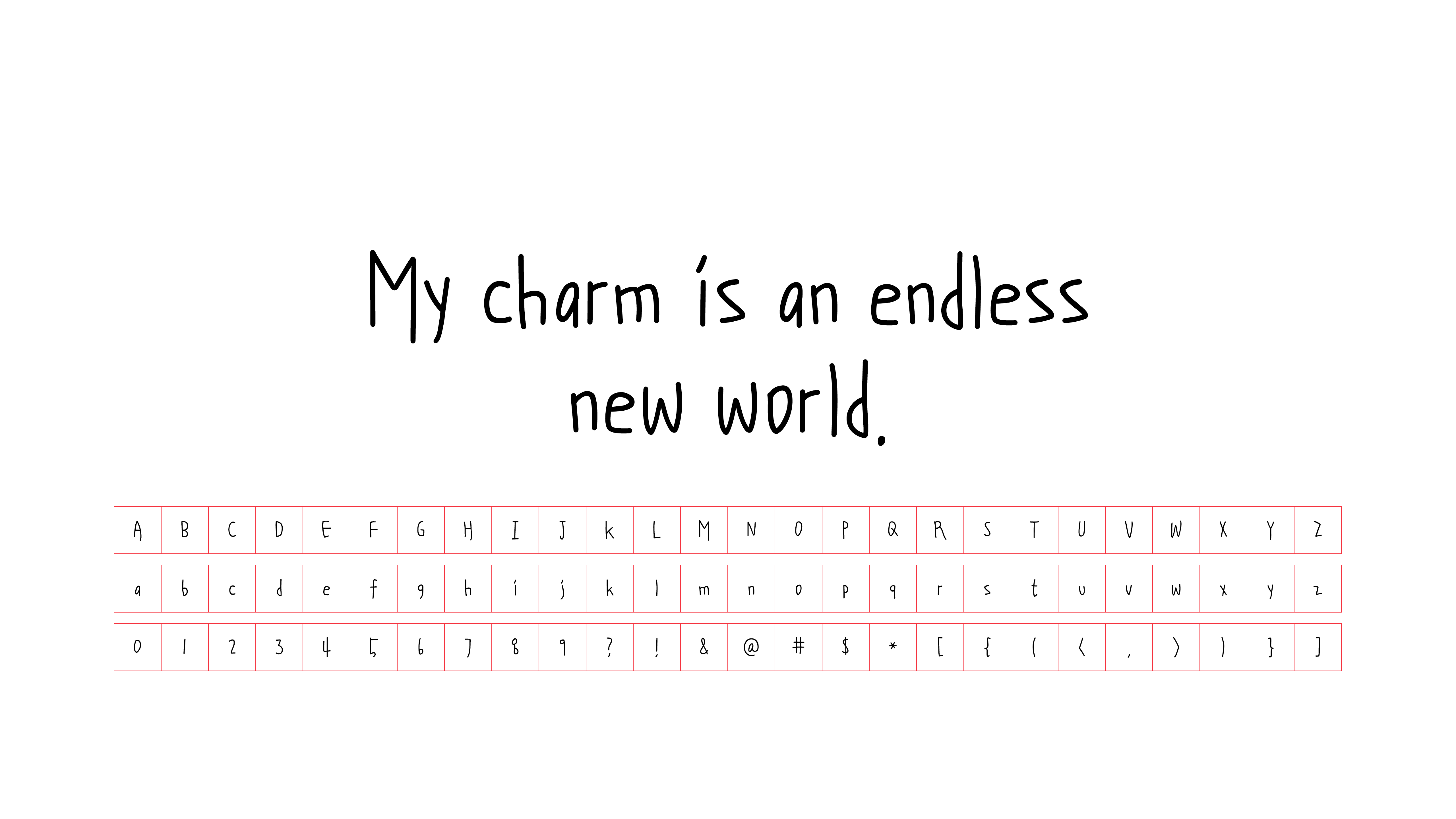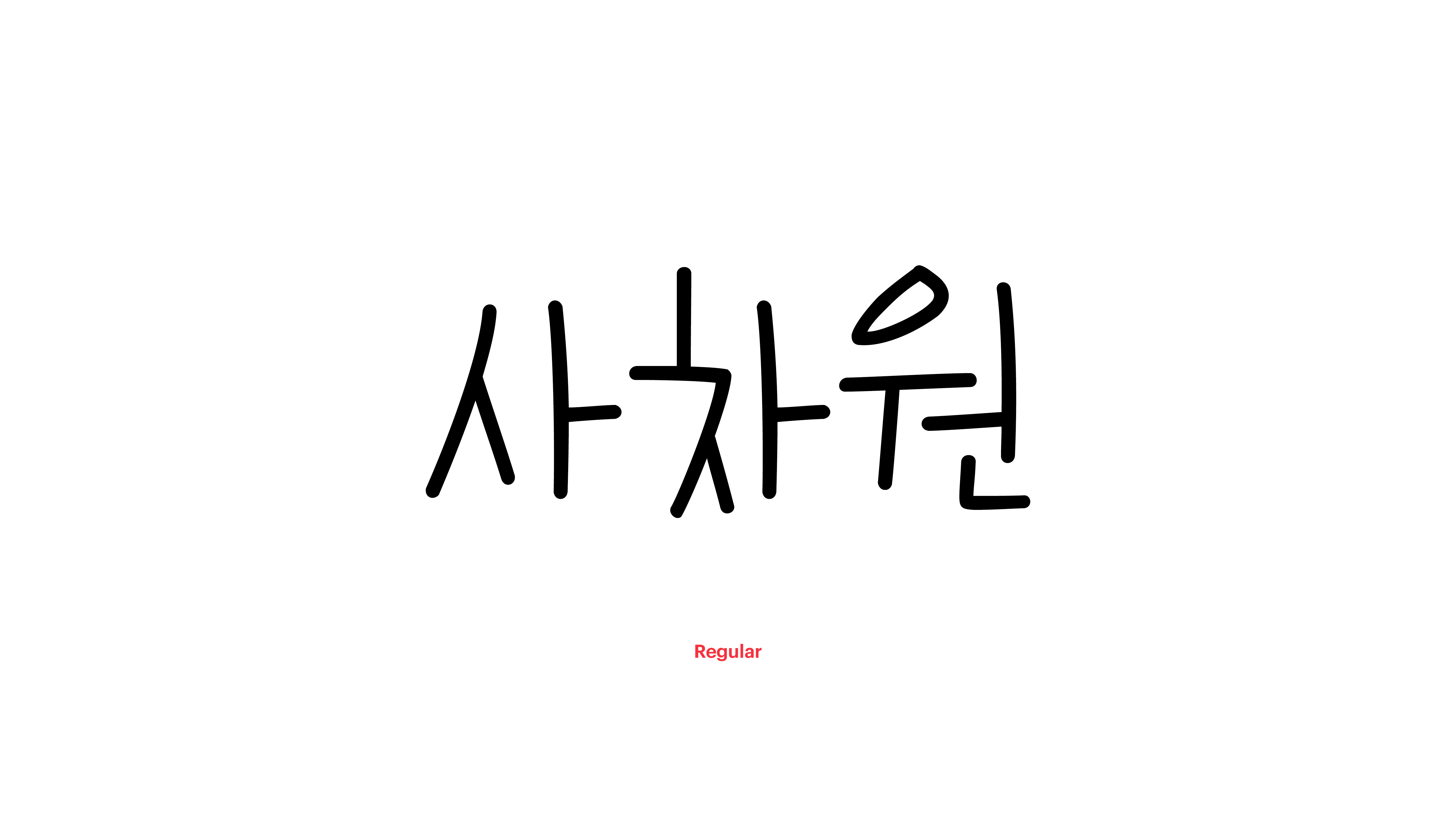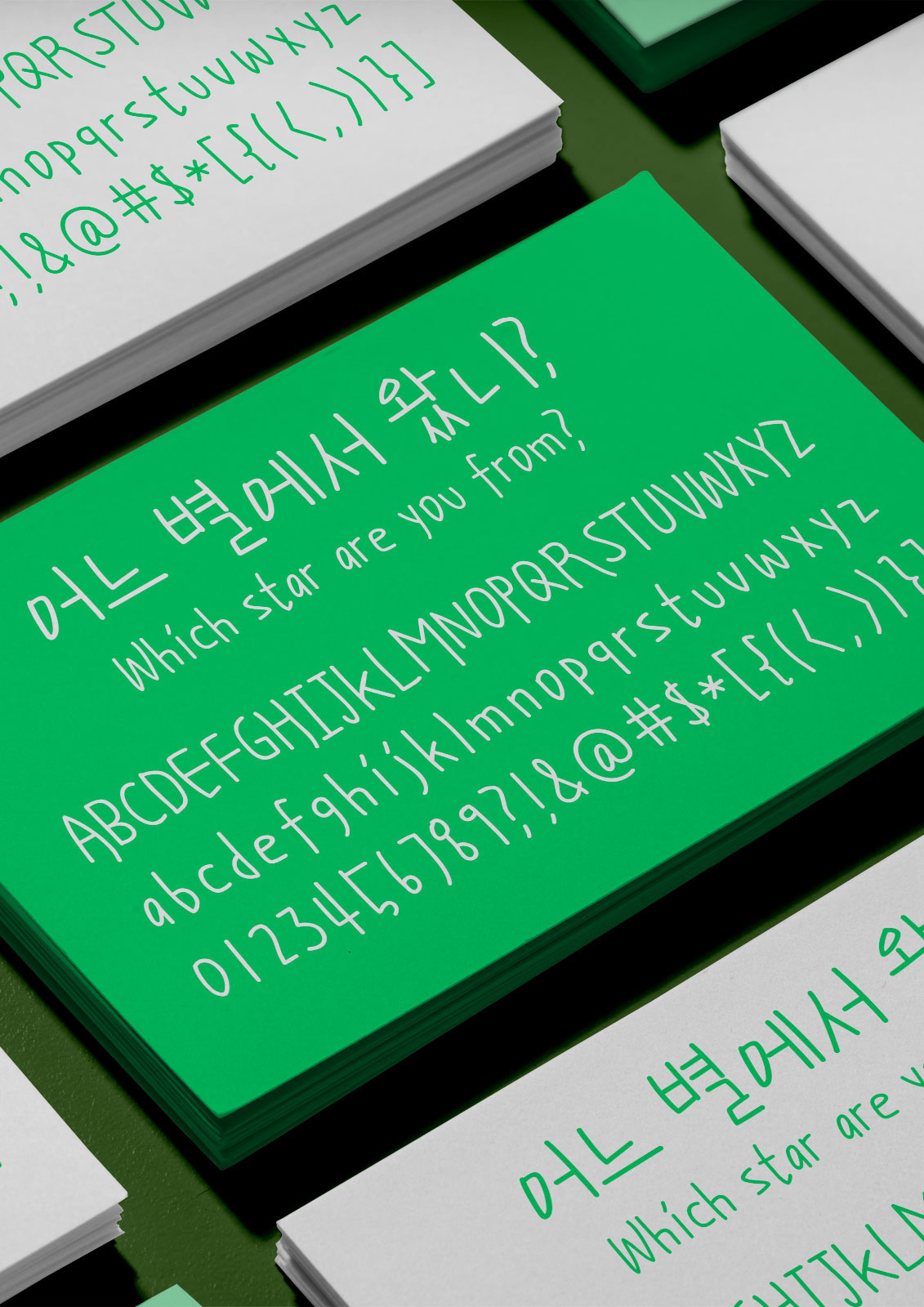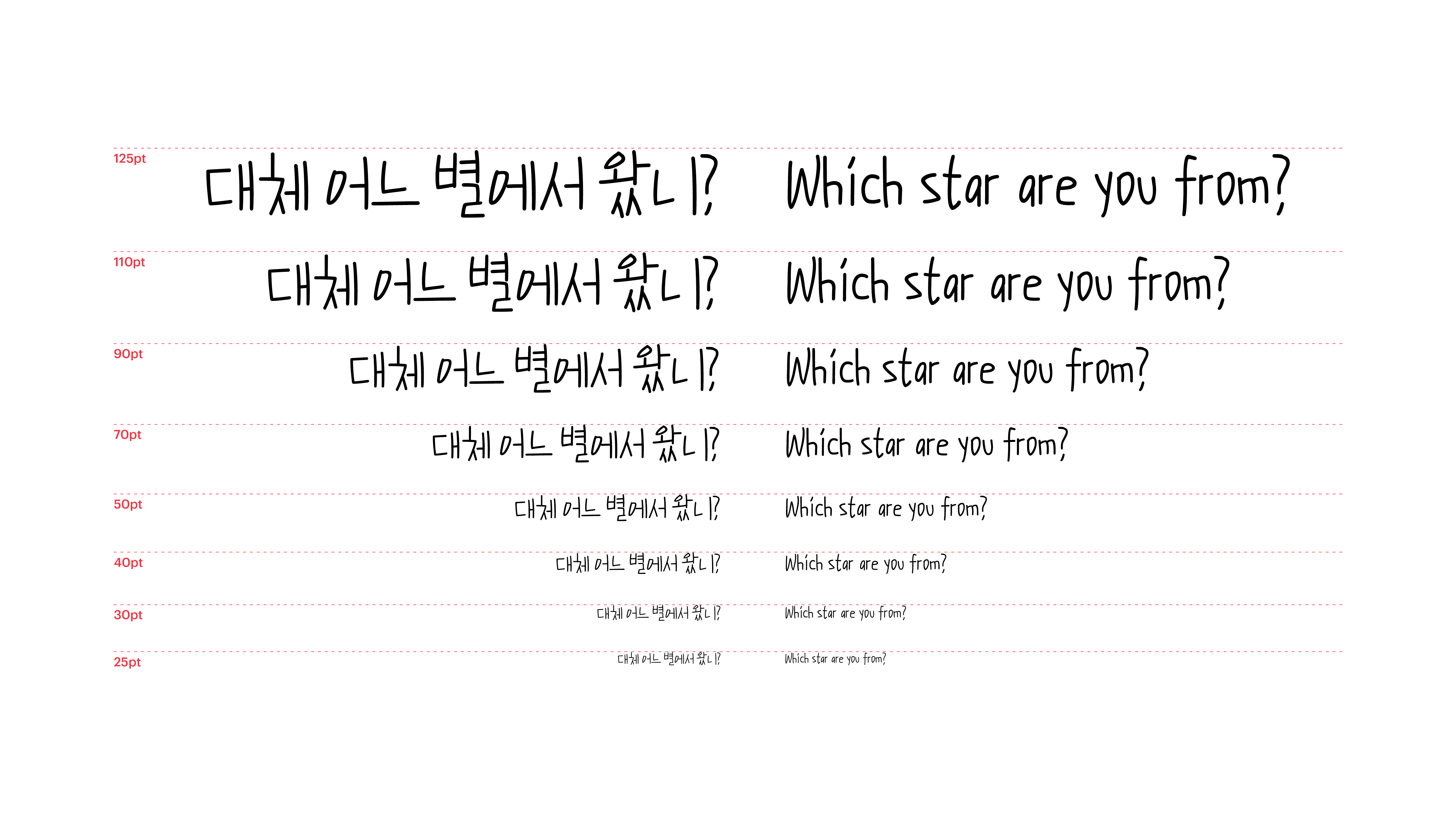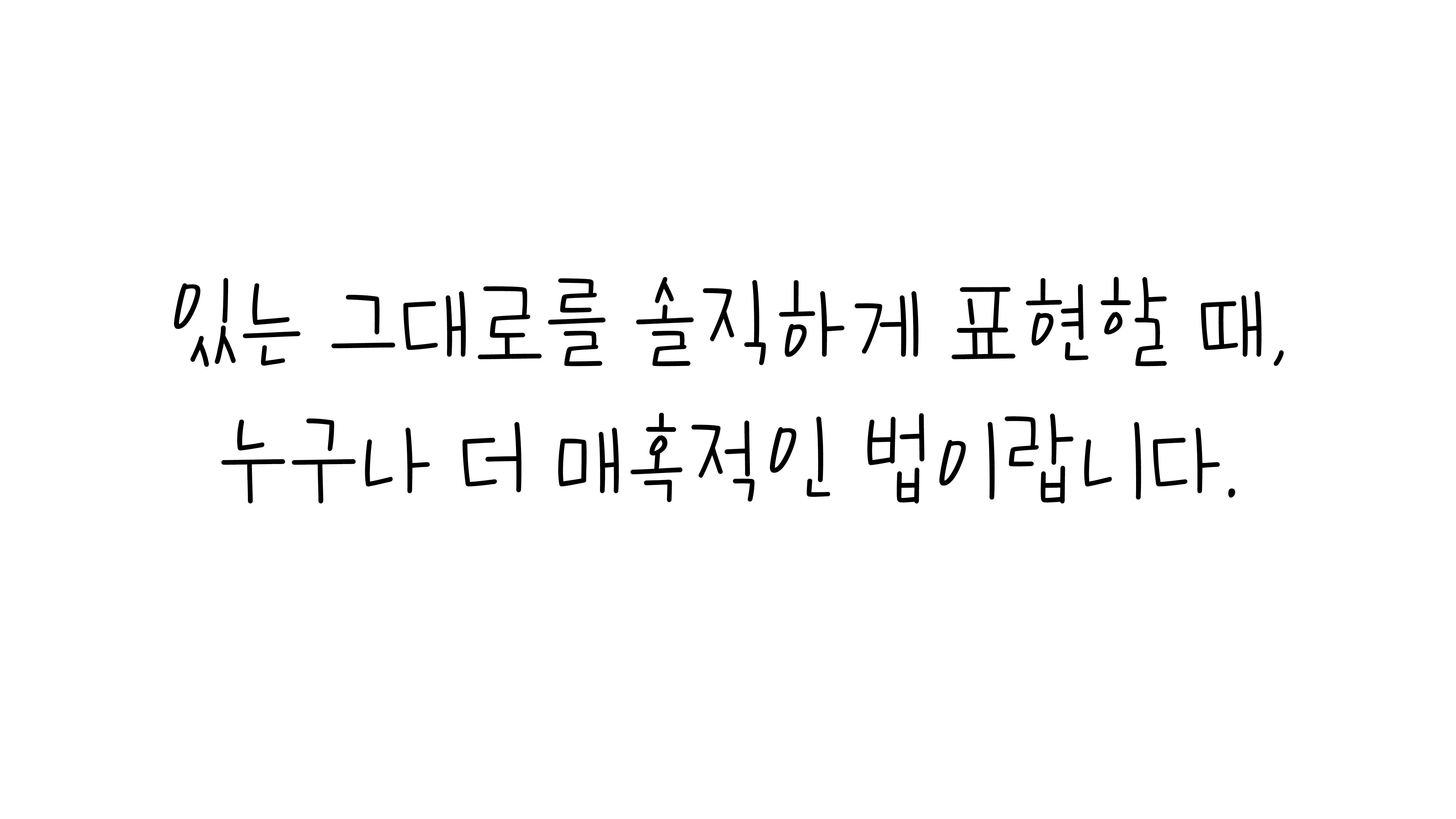
사차원
Yoon 사차원
굳이 뭔가를 더하려고 하거나 빼려고 하지 않아도 괜찮아요. 있는 그대로를 솔직하게 표현할 때, 누구나 더 매혹적인 법이랍니다. “대체 어느 별에서 왔니?” 묻고 싶어지는 이 기묘한 폰트를 좀 보세요. 어쩐지 몰입해서 읽게 되지 않나요? 우리가 잘 모르는 새로운 차원의 문을 열어줄 것 같기도 하고요.